Шрифты для книги. 10 отличных шрифтов для макета вашей книги
Шрифты для книги — это наборы графических символов, используемых для набора текста в книге. Выбор подходящих шрифтов для книги важен для создания читабельного и приятного визуального опыта для читателей. Легко забыть, что книжные шрифты, которые мы видим сегодня, являются результатом сотен лет эволюции дизайна. От дизайнов, имитирующих почерк, до четких, чистых шрифтов с засечками, которые вы найдете в большинстве публикаций, современные шрифты — это кульминация веков, когда люди объединяли форму и функцию во что-то великолепное, но пользователи этого почти не замечают. Конечно, как автору вы не можете избежать такого же безразличия: выбор шрифта — важный шаг в дизайне вашей книги — как внутри, так и снаружи .
Что такое шрифт?
Прежде чем мы начнем, давайте проясним терминологическую деталь. Настоящие эксперты по шрифтам быстро укажут на то, как термин «шрифт» часто неправильно используется в повседневной, не технической беседе.
Для типографов «гарнитура» — это разные надписи, такие как Times New Roman и Arial. «Шрифты», с другой стороны, представляют собой вариации размера, веса и стиля гарнитуры, например, шрифт Times New Roman размером 12 пт и курсив Arial 14 пт. Однако для удобства мы будем использовать термин «шрифт» для обозначения как общих стилей шрифтов, так и их вариаций.
Как выбрать книжный шрифт? Шрифты для книги
Выбор «правильного» шрифта для основного текста книги часто сводится к индивидуальному вкусу. За исключением нескольких универсально оскорбленных шрифтов — cough cough, Comic Sans — можно рассматривать практически любой разборчивый шрифт. Сказав это, есть несколько вещей, о которых любой взыскательный дизайнер книг захочет иметь в виду.
Он должен быть читабельным
Представьте себе красивый стул . Возможно, это самая красивая вещь, на которую можно смотреть, но если на ней неудобно сидеть, тогда какая от этого польза? То же самое и со шрифтами. Хотя вы, очевидно, хотите, чтобы ваш шрифт хорошо смотрелся на странице, он также должен выполнять свою работу и быть легко читаемым, чтобы читатели могли погрузиться в ваши слова, не отвлекаясь и не пытаясь расшифровать, о чем говорится.
С засечками или без засечек? Шрифты для книги
Хотя вы можете не знать шрифта с засечками по имени, вы наверняка заметили эти маленькие линии или штрихи на концах букв в некоторых шрифтах, таких как Times New Roman .
Предположительно, засечки ведут взгляд от одной буквы к другой, делая процесс чтения более легким и менее утомительным — хотя на самом деле нет большого количества научных доказательств в пользу этого. Но в результате этой теории вы часто будете видеть шрифты с засечками, используемые для больших объемов текста, в то время как шрифты без засечек — буквально без засечек — обычно зарезервированы для более коротких фрагментов текста, таких как заголовки глав и заголовки.
Все это говорит о том, что люди легко приспосабливаются, и ваш читатель должен иметь возможность адаптироваться практически к любому шрифту после главы или около того. Если есть выбор шрифта, который, по вашему мнению, действительно улучшит или выделит вашу работу, не стесняйтесь выбирать новизну, а не условность.
Стиль по-прежнему важен . Шрифты для книги
Чтобы привлечь внимание читателя, вам понадобится современный, стильный шрифт, который понравится, но это довольно субъективно, поэтому снова выберите тот, который вам нравится. На выбор шрифта также должно влиять содержание вашей книги. Вы можете проявить творческий подход к названиям и заголовкам, которые лучше передают дух или жанр вашей книги. Или даже изо всех сил и сделайте что-нибудь необычное с основным текстом — если это имеет смысл для макета вашей книги . Многие из так называемых правил шрифтов могут быть нарушены, если ситуация действительно этого требует.
Используйте шрифты, чтобы рассказать историю
Например, в романе « Интерьер китайского квартала» рассматривается идея приведения типов и стереотипов в киноиндустрии. Чтобы придать ей ощущение голливудского фильма, книга написана в формате сценария с использованием Courier в качестве стандартного шрифта.
Излишне говорить, что это необычный выбор для романа — использование определенного шрифта, который часто категорически не рекомендуется использовать при наборе книг. Но в случае с Внутренним китайским кварталом Courier — это очень преднамеренный выбор, служащий определенной цели и способствующий влиянию самой книги. Это лучший пример, когда можно отказаться от типичных условных обозначений шрифтов в пользу эффекта.
Совет от профессионала: некоторые сайты, такие как MyFonts, позволяют вам тестировать образцы текста с определенным шрифтом, прежде чем вы сделаете решительный шаг и купите его. Это особенно полезно при выборе между очень похожими шрифтами, поскольку вы не сможете уловить тонкие различия, пока не увидите их в более крупном блоке текста.
10 блестящих книжных шрифтов
1. Garamond. Шрифты для книги
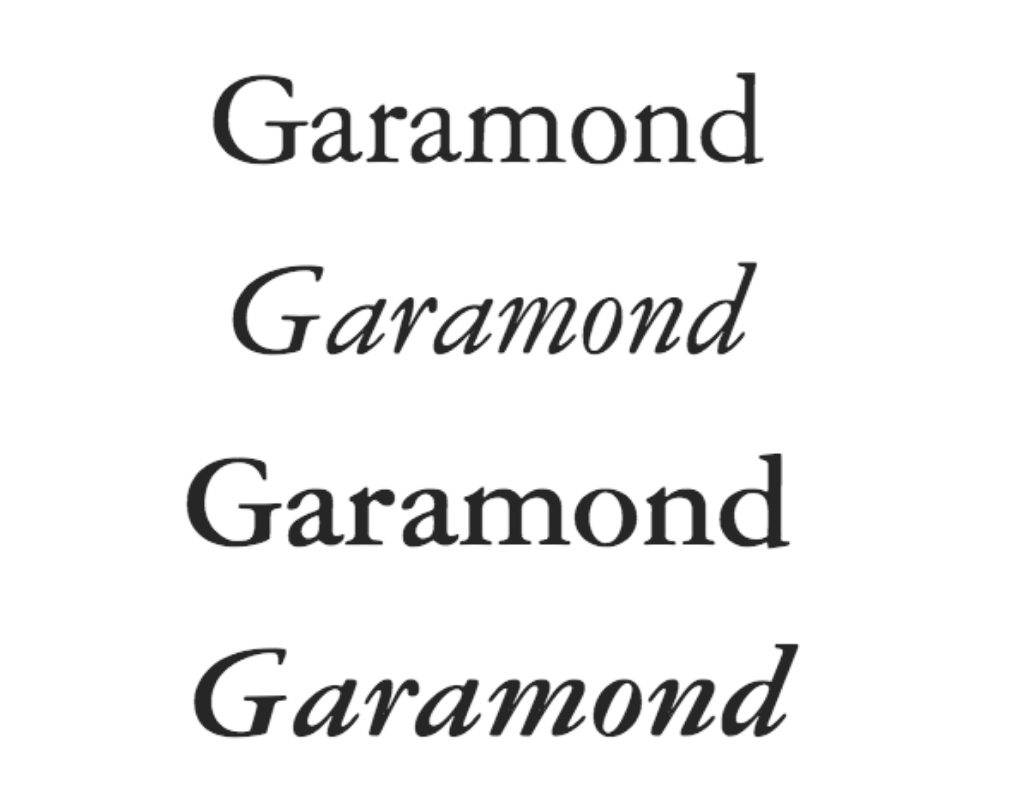
Краткий факт: это семейство шрифтов, созданное по мотивам работ выдающегося гравера 16-го века Клода Гарамонда, стало популярным в качестве стандартного варианта в Microsoft Word.
Если бы этот шрифт был персонажем: Гарамонд, детектив 1920-х годов, скрывающийся в тени переулка Нью-Йорка, ожидающий, когда коррумпированный окружной прокурор покинет ночной клуб, связанный с мафией, — прямо как дома в захватывающем триллере .
2.Caslon/ Шрифты для книги
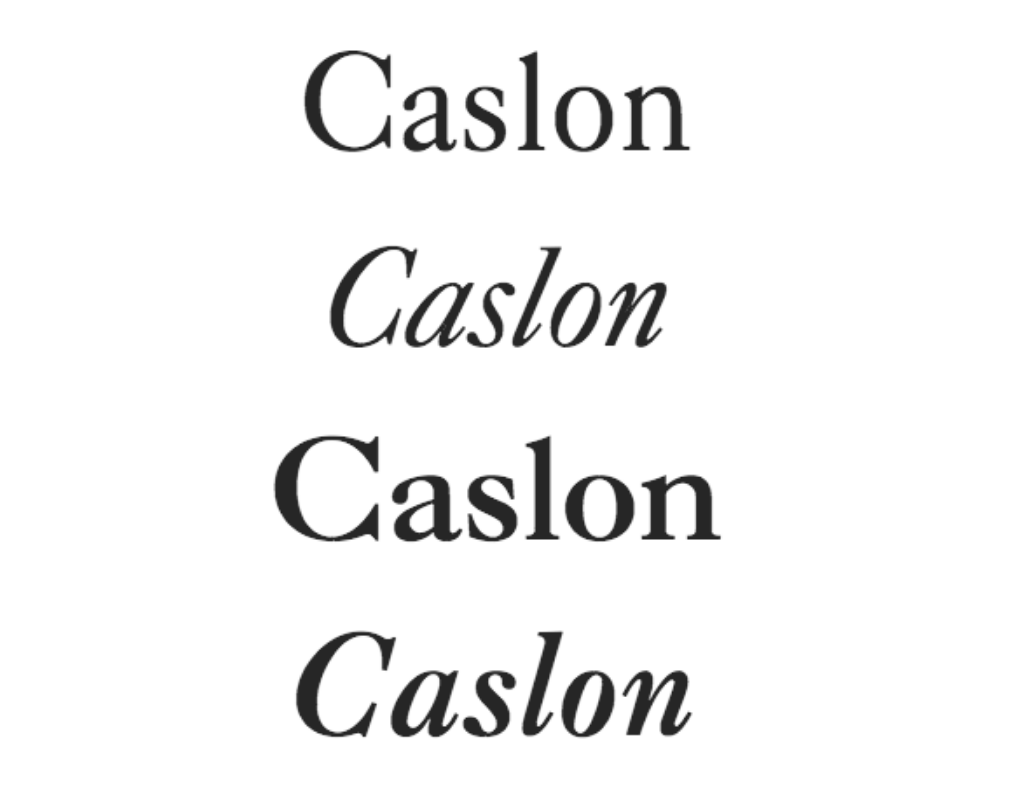
Краткий факт: дизайнер Caslon Уильям Кэслон возглавил разработку английского типографского стиля, вызвав отход от импортированных голландских шрифтов, которые были распространены в Англии в то время.
Если бы этот шрифт был персонажем: Кэслон, серьезный профессор в очках, которого до сих пор навещают бывшие студенты, потому что они чувствуют, что всем своим успехом они обязаны ему. Ясный и надежный, Caslon отлично подходит для документальной литературы .
3. Baskerville . Шрифты для книги
Быстрый факт: Баскервиль был новинкой XVIII века благодаря контрастным толстым и тонким мазкам. Джон Баскервиль, создатель этого шрифта, находился под сильным влиянием своего опыта в каллиграфии.
Если бы этот шрифт был персонажем: Баскервиль , хозяйка поместья, управляет домом, как плотным кораблем. Слуги дрожат под ее железным взглядом — но ее ледяная внешность тает, когда она садится за мольберт. Баскервиль пробирается по коридорам исторической фантастики.
4. Sabon. Шрифты для книги
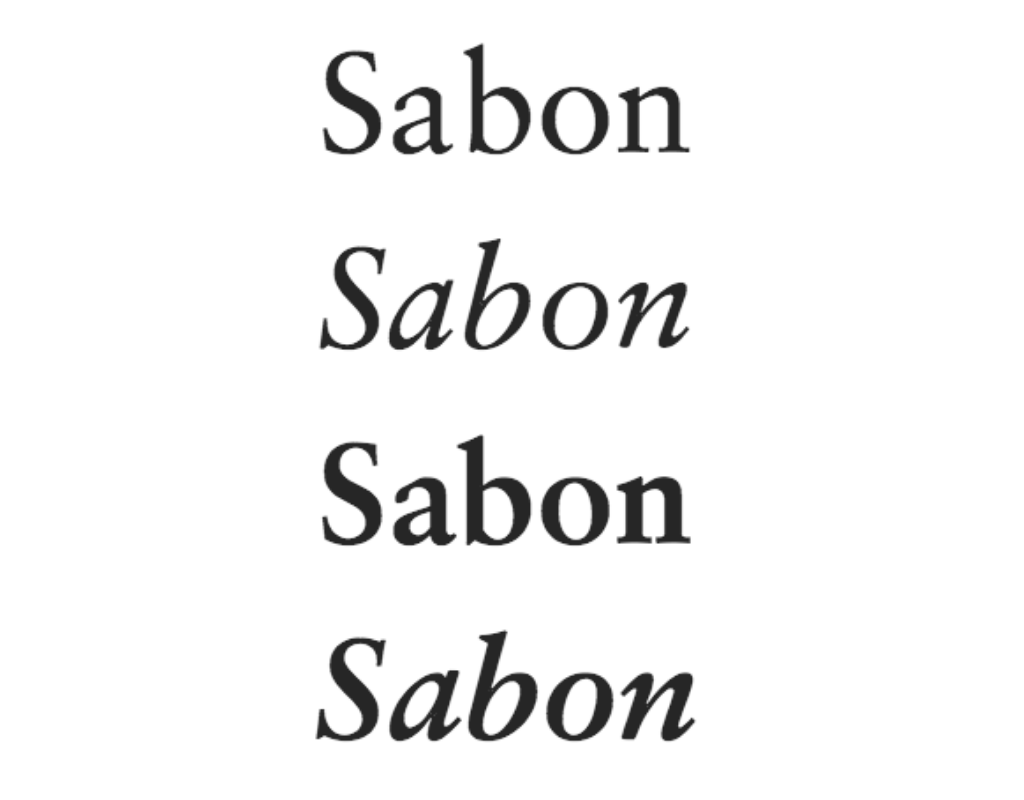
Быстрый факт: из изображения выше вы можете заметить, что каждый вариант шрифта Sabon имеет точно такой же межбуквенный интервал (или трекинг , как его называют типографы). Это следствие ограничений наборных станков для чугуна, использовавшихся на момент его разработки.
Если бы этот шрифт был персонажем: Сабон, застенчивый безнадежный романтик, крадет взгляд на возлюбленную, которая не знает своих истинных чувств, прежде чем, наконец, набраться смелости и сказать «привет». Отсюда возникает сладкий и мечтательный роман . Шрифты для книги
5. Dante
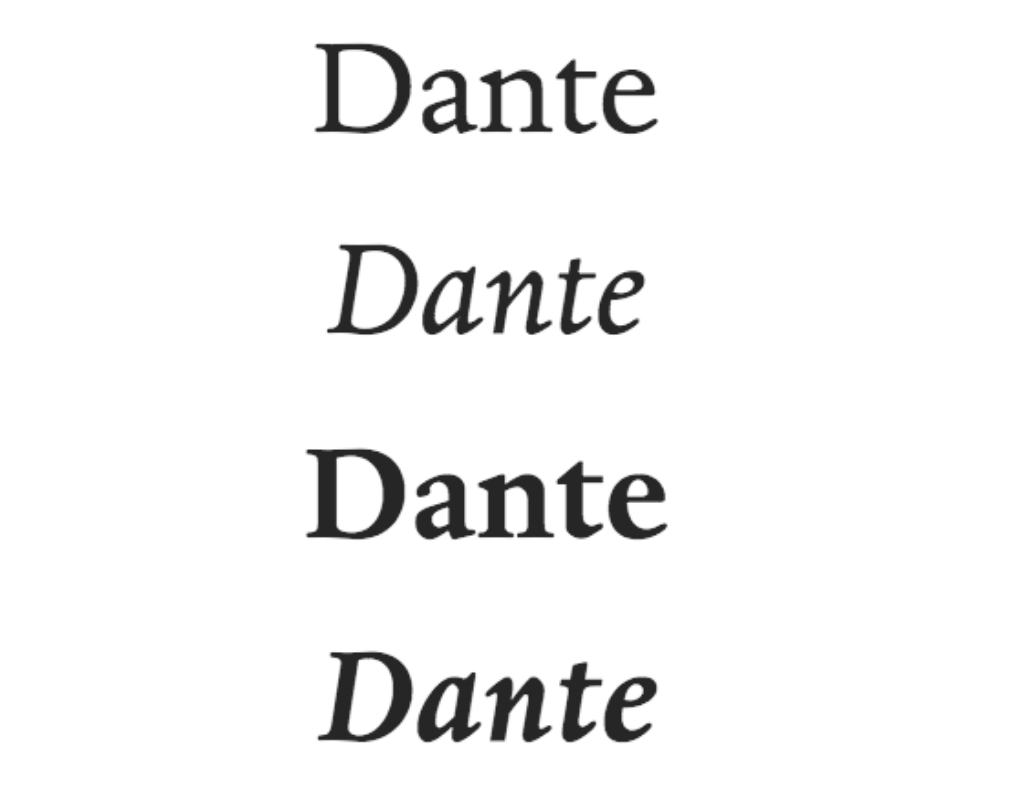
Краткий факт: Данте был первоначально разработан в середине 20-го века для эксклюзивного использования Officina Bodoni, частной прессой, которой восхищаются коллекционеры книг по всему миру.
Если бы этот шрифт был персонажем: Данте, озорным подростком, который только что нажал запретную большую красную кнопку в диспетчерской. Космический корабль кренится. Данте осмеливается отправить вас в увлекательное научно-фантастическое приключение . Шрифты для книги
6. Bembo
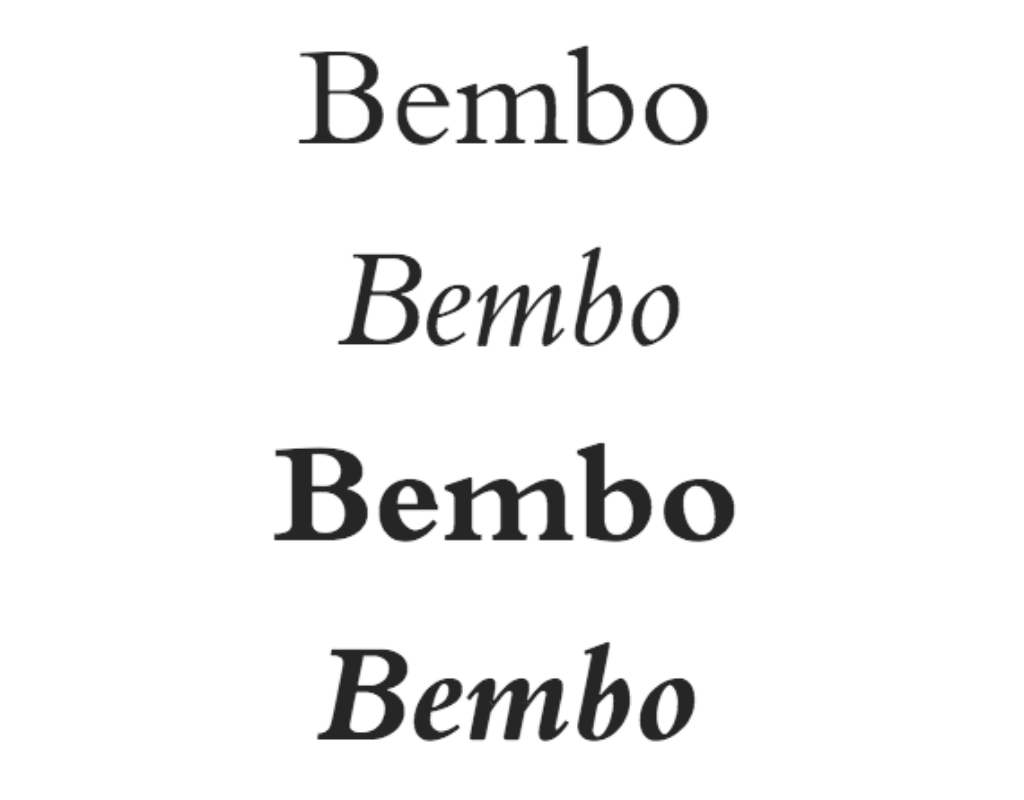
Быстрый факт: в отличие от многих гарнитур, названных в честь их дизайнеров, Bembo берет свое имя от автора, который первым использовал его в публикации: итальянского поэта Пьетро Бембо.
Если бы этот шрифт был персонажем: Бембо, увлеченный странствиями фотограф, обедающий в одиночестве в тени пальмы, третья порция жареной рыбы уже в пути — но сможет ли он действительно заполнить пропасть внутри него? Bembo — отличный выбор для запоминающейся литературной фантастики .
7. Jason/ Шрифты для книги
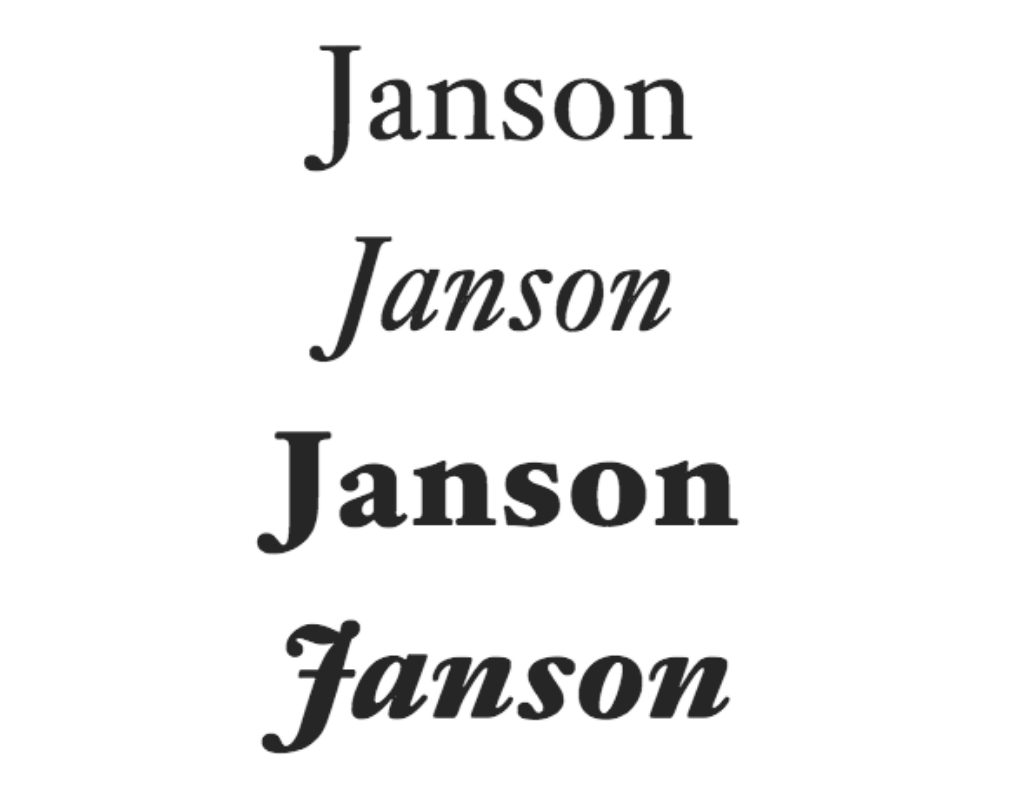
Быстрый факт: хотя этот шрифт на самом деле был разработан венгерским штамповщиком Миклошом Кисом, первоначально он был ошибочно приписан Антону Янсону, имя которого он носит до сих пор.
Если бы этот шрифт был персонажем: Янсон — мудрая старая душа, которая после долгих лет быстрой жизни музыканта променяла трубу на мастерок, в изобилии выращивая фрукты и овощи. Совершите путешествие по переулку памяти вместе с Янсоном в своих мемуарах .
8. Bison/ Шрифты для книги
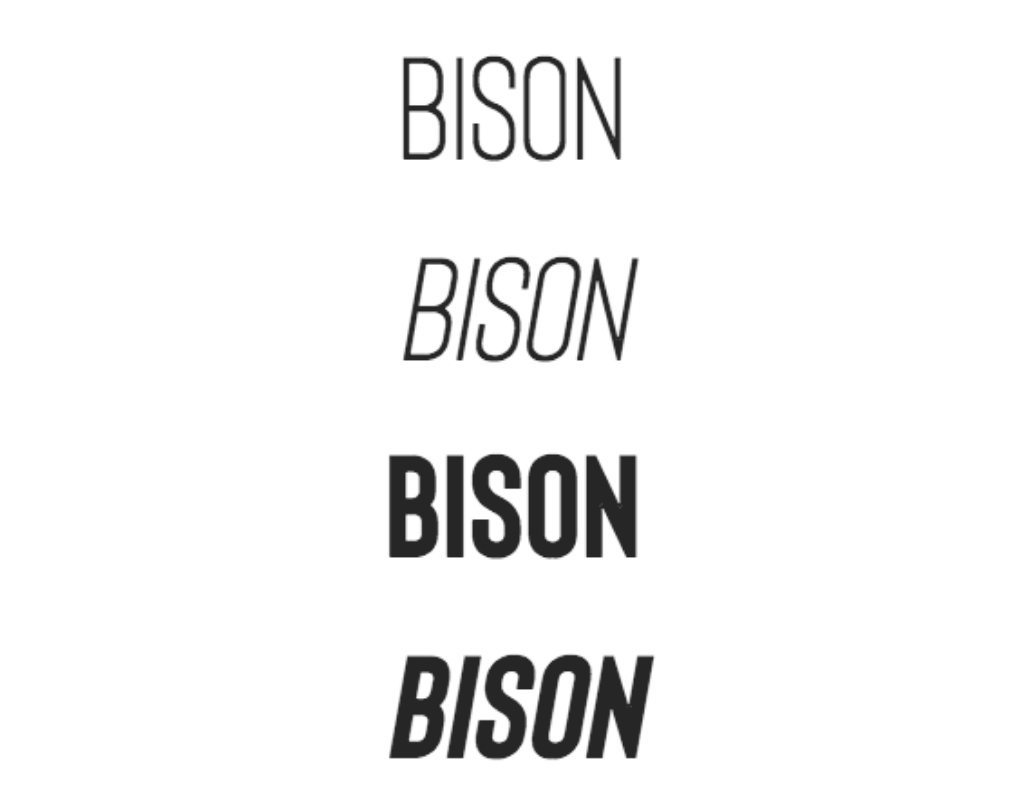
Быстрый факт: этот шрифт без засечек, состоящий только из заглавных букв, был вдохновлен животным, от которого он получил свое название. (Но, честно говоря, мы не видим сходства.)
Если бы этот шрифт был персонажем: Бизон, крупный и ответственный генеральный директор, поставил ноги на стол и смотрел на город с 90-го этажа. Bison привносит элегантность и уверенность в заголовки и заголовки.
9. Captain comic Шрифты для книги
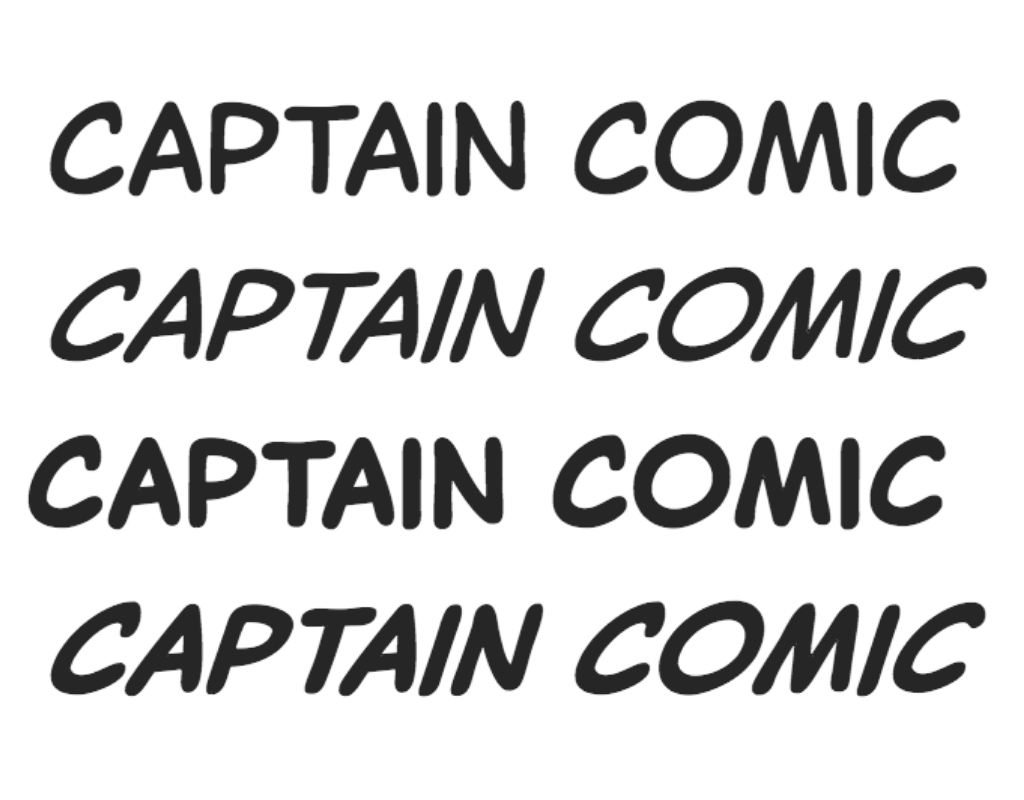
Быстрый факт: явно вдохновленный стилем букв, найденным на страницах комиксов , Captain Comic является сложной старшей сестрой Comic Sans. Используйте с осторожностью!
Если бы этот шрифт был персонажем: Captain Comic, бесстрашный герой, взбирается на башню с часами глубокой ночью — осознавая, какая опасность может поджидать наверху, но тем не менее бесстрашный. Captain Comic безраздельно властвует в насыщенном событиями графическом романе .
10. Pequena Pro. Шрифты для книги
Краткий факт: Pequena Pro была разработана в 2016 году Родриго Арайя Саласом и поддерживает как латиницу, так и кириллицу. (Послушайте, не все эти быстрые факты могут быть победителями.)
Если бы этот шрифт был персонажем: Pequena Pro, говорящий бегемот, ищет еды (как всегда), когда она встречает застрявшую на берегу семью сурикатов и предлагает помочь им пересечь реку. Pequena Pro восхитительна для детской книги .
Как получить доступ к книжным шрифтам
Самый простой способ найти наиболее подходящие шрифты для вашей книги — это обратиться к профессиональному дизайнеру. У них будет доступ к библиотекам шрифтов, и многие из этих экспертов могут даже создавать собственные шрифты , если ваш проект потребует этого.
Но если вы воспользуетесь подходом «сделай сам» к форматированию книги , тогда вам придется самостоятельно разрабатывать шрифты. Вот что нужно знать, если вы выбираете этот маршрут:
Вы не покупаете шрифт, вы его лицензируете. Если вы собираетесь печатать физические копии, а также публиковать электронные книги, вам необходимо подтвердить, что шрифт можно использовать в печати, а не только в цифровой работе (как некоторые из них). Шрифты для книги
Шрифты бывают связками. Здесь можно быстро переключиться на терминологию типографики — чтобы использовать все шрифты определенного гарнитуры (например, Caslon Regular, Caslon Bold и Caslon Italic), вам нужно купить все семейство шрифтов Caslon, по отдельности или как часть набора.
Бесплатно не всегда хорошо. Ссылки для загрузки бесплатных шрифтов иногда могут содержать вирусы. Также имейте в виду, что лицо, предлагающее бесплатный шрифт, может фактически не иметь права распространять его — и это может иметь последствия за их использование . Шрифты для книги
В связи с этим, вот несколько заслуживающих доверия сайтов, которые предлагают как бесплатные, так и платные шрифты:
Независимо от того, скачиваете ли вы шрифты бесплатно или покупаете их, обязательно внимательно прочтите Условия и положения, чтобы вы точно понимали, что вы можете и что не имеете права с ними делать.
У всех шрифтов есть время и место — да, даже Comic Sans — но этого места может не быть в вашей книге. Выполняя этот критический процесс выбора, убедитесь, что вы думаете о специфике своей книги и о том, чего именно вы хотите добиться с помощью шрифта.
Типография Азбука
Мы рады представить вам типографию «Азбука» — ваш надежный партнер в печати книг высокого качества. Мы специализируемся на профессиональной печати и издательском процессе, предлагая широкий спектр услуг для авторов, издателей и бизнес-клиентов.
Наша типография оснащена современным оборудованием и использует передовые технологии для достижения оптимальных результатов. Наш опытный и творческий персонал всегда готов воплотить в жизнь ваши идеи и помочь вам создать книгу, которая будет выделяться своим качеством и привлекать внимание читателей.
Мы предлагаем широкий выбор опций и услуг, включая цветную и черно-белую печать, различные форматы книги, разнообразные типы бумаги и обложек. Мы также предлагаем услуги верстки, редактирования текста, дизайна обложек и творческой поддержки, чтобы помочь вам достичь желаемого эстетического и качественного результата.
Наша команда гарантирует высокий профессионализм, точность и соблюдение сроков. Мы понимаем, что каждая книга уникальна, и наша цель — обеспечить ваш успех и удовлетворение от конечного продукта.
Если вы ищете надежного партнера для печати книг, обратитесь к нам в типографию «Азбука». Мы готовы воплотить вашу книгу в жизнь с безупречным качеством и профессиональным подходом. Свяжитесь с нами сегодня и доверьте нам свою печать книг.
Цена изготовления книг и блокнотов формат А5 (148х210 мм). Твердый переплет
| Тираж/Станицы | 50 | 100 | 200 | 300 |
|---|---|---|---|---|
| 150 | 216 | 200 | 176 | 163 |
| 250 | 252 | 230 | 203 | 188 |
| 350 | 287 | 260 | 231 | 212 |
Формат А5 (148х210 мм)
Обложка: палитурный картон 2 мм. Печать 4+0. (цветная односторонняя). Ламинация.
Форзацы — без печати.
Внутренний блок : бумага офсетная плотностью 80 гр/кв.м. Печать 1+1 (черно-белая печать с двух сторон)
Крепление — нитка.
Цена за 1 шт при тираже.
Цена изготовления книг и блокнотов формат А4 (210х297 мм). Твердый переплет
| Тираж/Станицы | 50 | 100 | 200 | 300 |
|---|---|---|---|---|
| 150 | 400 | 380 | 337 | 310 |
| 250 | 470 | 440 | 392 | 360 |
| 350 | 540 | 480 | 441 | 410 |
Формат А4 (210х297 мм)
Обложка: палитурный картон 2 мм. Печать 4+0. (цветная односторонняя). Ламинация.
Форзацы — без печати.
Внутренний блок : бумага офсетная плотностью 80 гр/кв.м. Печать 1+1 (черно-белая печать с двух сторон)
Крепление — нитка.
Цена за 1 шт при тираже.
Каким шрифтом печатают книги?
Выбор шрифта для книги — проблема, которая волнует начинающих создателей художественной и научной литературы.
Задача дизайнера книжной типографии состоит в том, чтобы подобрать идеальный шрифт для вашей книги. Главное правило того, что вы прогадали со стилем шрифта, — это удобство чтения. Когда вы читаете книгу, вы погружаетесь в историю, наполняетесь эмоциями автора, познаете новую информацию, и последнее, что вы должны замечать — как выглядит шрифт.
Если вы решили самостоятельно заняться оформлением рукописи, прочтите несколько важных советов по лучшим шрифтам для книги от типографии “Принтлето”.
Какой размер шрифта используется в книгах?
Шрифт — неотъемлемая часть в создании композиции книги. Книжные дизайнеры разделяют два понятия: гарнитура и шрифт.
Шрифт — это определенный образец, например, Helvetica Narrow Italic. А гарнитурой обозначают набор шрифтов одного рисунка, но разных размеров (кеглей) и начертаний. Например, Helvetica — это гарнитура.
Шрифт также делят на 2 группы: наборный и рисованный. Наборный шрифт используется для самого текста издания. Рисованный шрифт применяется для визуального оформления, дизайна книги, в частности, на обложке, переплете и титульном листе. Рисованный шрифт создает уникальный стиль книжного произведения.
При выборе шрифта учитывайте 3 особенности: гарнитуру, начертание и кегль.
Наборный текст рекомендуется печатать обычным, курсивным, полужирным или курсивным полужирным шрифтом в выбранной гарнитуре. Добиться запоминающегося дизайна можно используя всего пару шрифтов.
Что ещё влияет на выбор шрифта? Конечно, бумага. Если у вас мелованная бумага, то не используйте тяжелые, контрастные шрифты, они выглядит броско. А на газетной бумаге с трудом читается тонкий и изящный шрифт.
Чтобы вашу книгу смог прочитать каждый без лишнего напряжения и «вглядывания» в буквы, важно подобрать шрифтовой кегль. Размер кегля исчисляется в пунктах (1 пункт = 0,376мм).
Для каждого кегля есть свое персональное название: кегль 6 пунктов — бриллиант; кегль 4 пункта — диамант; кегль 6 пунктов — нонпарель; кегль 7 пунктов — миньон; кегль 8 пунктов — петит; кегль 9 пунктов — боргес; кегль 10 пунктов — корпус; кегль 12 пунктов — цицеро; кегль 14 пунктов — миттель.
Для каждого типа книжного издания определен наиболее читаемый размер кегля. Так, для художественной литературы подходит 10-12-ый кегль. Для остальной печатной продукции оптимальным считается 9-14-ый кегль.
Не забывайте и о том, что размер наборной строки тоже играет свою роль в удобочитаемости. Рекомендуем использовать не более 50-55 знаков в одной строке.
На выпуск книжных изданий существует ГОСТ, по которому определяется кегль и стиль шрифта. В большинстве печатных изданий используют Times New Roman, Garamond, Bodoni, Academy, Georgia.
Роль шрифта в оформлении книги
Шрифт — способ передачи текста в книге. Это его главная и существенная роль. Подобрать должным образом шрифт — задача непростая, но по силу каждому. Следуйте простым правилам подбора шрифта, и тогда всё получится. А ниже мы подобрали основные принципы, на которые влияет шрифт.
Шрифт с засечками и без. Для основного текста издания рекомендуем использовать шрифт с засечками или без засечек, потому что такие шрифты являются «классическими» и не вызывают дискомфорта при длительном чтении. Декоративные шрифты подходят для заголовков, оглавления или других элементов книги, на которых нужно заострить внимание.
Ненавязчивость. Подбирайте шрифты без сложных буквенных форм. «Кричащие» о своей уникальности шрифты отвлекают читателя и не дают сосредоточиться на мысли, которую преподносит автор в тексте.
Печатные шрифты. Courier и другие шрифты, которые используются в печатных машинках, — это моноширинные шрифты. Отличить их можно по одинаковой ширине всех знаков. Избегайте таких шрифтов для создания основного текста книги. В качестве исключения, моноширинные шрифты используют для заголовков глав, и в других случаях, где вам требуется характерный шрифт.
Как выбрать шрифт для детской книги?
Если вы пишите детскую книгу и не знаете, какой размер шрифта лучше подойдет, то прочтите рекомендации по выбору шрифта для каждой возрастной группы. Для детей дошкольного возраста (до 7 лет) подойдет шрифт в 16 или 20 пунктов, так как дети только начинают читать и знакомиться с буквами, их должно быть хорошо видно.
Для детей первой младшей группы (7-9 лет) 14 и 16 пунктов для первоклассников, 12 и 14 пунктов для второго класса.
Для детей второй младшей группы (10-11 лет) 11 и 12 пунктов для третьего класса, 10 и 11 пунктов для четвертого класса.
Дети среднего и старшего возраста (12-17 лет или 5-11 классы) могут читать шрифт любого размера.
Лучшие шрифты для чтения на электронной книге eBook
При чтении электронных книг приходится проводить много времени уставившись в экран. Поэтому внешний вид текста имеет большое значение! Правильный выбор шрифта может улучшить общее впечатление от чтения. Какой шрифт поможет вам читать быстрее и меньше напрягать глаза? Когда речь заходит о шрифтах, выбор очень велик. Некоторые шрифты приятны для глаз, некоторые обладают индивидуальностью, а некоторые легко читаются.
Если в вашей электронной книге много текста, самыми удобными для чтения будут шрифты с засечками, такие как Times New Roman, Garamond, Baskerville и Caslon. Эти старые традиционные шрифты уже давно используются для книг и по-прежнему являются отличным выбором для электронных книг. Важно, чтобы шрифт был удобен для чтения, тем более что люди будут читать его в цифровом формате на экранах любого размера. Шрифты с засечками более разборчивы и привлекательны для читателя.
Вот несколько лучших шрифтов, которые эксперты рекомендуют для электронных книг.
Как правильно выбрать шрифт для книги?
— Конечно, книга — это, в первую очередь, носитель информации и хранитель знания. Но в культуре всегда важна коммуникация. И графический дизайн в определенном смысле осуществляет функцию перевода. С читателем необходимо коммуницировать. Если дизайн хороший, он облегчает доступ к культуре. Если он сделан плохо и небрежно, культурный материал рискует быть утраченным.
— Получается, что, издавая книгу в переводе на другой язык, дизайн книги также нужно определенным образом «переводить»?
— Существуют вещи, которые можно передать «один к одному». Например, для книги, изданной на немецком языке, существуют правила набора текста или форматирования, которые можно «перевести», работая с кириллицей. В некоторых своих книгах я часто обращаюсь к метафорам в концептуальной структуре издания, разным возможностям построения в нем нарратива. В одной моей работе, например, один рассказ воспроизводится трижды, но с различных точек зрения. Такие вещи будет легко адаптировать при «переводе». Однако кое-что (например, ту же типографику), вполне вероятно, придется переделать полностью.
— Может ли профессиональный дизайнер иметь свои предпочтения в смысле материала, с которым работает, или же он должен уметь спроектировать издание на любую тему?
— Мое собственное мнение всегда играет существенную роль. Есть клиенты, с которыми я ни за что не стал бы сотрудничать, с другими по завершении работы мы становились хорошими друзьями. То же касается изображений. Работа по их отбору всегда внушительна и масштабна. Например, во время работы над одной книгой на нас свалилось около десяти тысяч произведений одного художника, но в издании мы смогли опубликовать лишь шестьсот. В этом случае, конечно же, мы глубоко были вовлечены в процесс отбора.
Толщина шрифта придает «толщину» и вес самому изданию. Книга становится высказыванием. И это важно, потому что она посвящена сквотам, уличным протестам, демонстрациям.
— Мой вопрос скорее о специализации.
— Область, которой я занимаюсь, можно обозначить как «книги и бренды» (books and brands). Кроме того, я преподаю дисциплину, которая называется «дизайн изданий» (editorial design). Это очень широкое понятие: сюда входят не только книги, но и газеты, журналы и в некотором смысле движущиеся изображения, если включить сюда еще и интернет-сайты. С другой стороны, мой интерес определенным образом сфокусирован, потому что моей страстью является создание и написание шрифтов.
Не могу сказать, что круг сотрудничества студии Hubertus Design, где я работаю, очень узок. Мы работаем с архитекторами, художниками, учеными, выпускаем литературные и экономические издания и не только. Современному графическому дизайнеру необходимо ориентироваться в огромном массиве информации. Одновременно с этим существует спрос на специализированный, узко заточенный дизайн для конкретных профессиональных областей. Часто мы работаем внутри разветвленных сетевых структур. Разумеется, ты не можешь уметь все, но ты должен понимать, где найти необходимую информацию и как связаться со специалистом, помощь которого тебе в данный момент необходима.
— Вы говорили, что дизайн выступает в роли переводчика. Но при этом в другом месте вы высказывали мнение, что значительная часть графического дизайна очень провинциальна. Может, она просто отражает особенности конкретной локальной культуры?
— В моих словах нет никакого противоречия, потому что дизайн, который я называю провинциальным, не имеет отношения к местной специфике. Если работа отвечает характерным локальным запросам, проблемам или вызовам, я всячески это приветствую. Но «провинциальное», напротив, несет в себе наиболее неспецифическое. Такие вещи обычно проходят по ведомству декора. Они поверхностны, непродуманны, и за ними не стоит никакой определенной позиции.
— Хотел спросить вас про конкретную книгу, выпущенную студией Hubertus Design, — издание «Wo-Wo-Wonige». Оно представляет собой докторскую диссертацию Томаса Штаеля, посвященную активистским движениям в Цюрихе после 1968 года. Как по-вашему, может ли дизайн сам по себе выполнять критическую функцию, быть критическим?
— Конечно, да, очень даже может. В некотором роде он всегда таковым и является. Дизайн всегда был тесно связан с вопросами политики. С другой стороны, если речь заходит о дизайне изданий или книг, пространства для маневров остается не так много. Дизайн ни в коем случае не может становиться барьером между читателем и текстом, но должен «поддерживать» передаваемое содержание. И если он сам вдруг начинает перевешивать, он просто перестает работать.
Книга «Wo-Wo-Wonige», которую вы упомянули и которая получила Федеральную швейцарскую премию в области дизайна, в этом смысле особенно интересна. Во-первых, она достаточно легко написана. Во-вторых, была проделана огромная работа. Автор посвятил ей много лет и собрал уйму материала, который, конечно же, невозможно было опубликовать в издании целиком. Текст в ней набран шрифтом Monotype Grotesque BoldExtended. Этот яркий полужирный шрифт, и в текстовых изданиях он обычно никогда не используется. Именно за это мою работу больше всего критиковали — что книга толщиной почти в пятьсот страниц отпечатана подобным образом.
Чем c более ярким и гетерогенным материалом ты работаешь, тем скромнее тебе приходится быть как дизайнеру.
Книга при этом получилась очень читабельной. Она настраивает на очень хороший темп и скорость восприятия. А толщина шрифта придает «толщину» и вес самому изданию. Книга становится высказыванием. И это важно, потому что она посвящена сквотам, уличным протестам, демонстрациям. Было бы просто неверным использовать более «мягкий» шрифт для такой импульсивной и агрессивной темы.
При этом, делая книгу, я полностью отказался от курсива. Если какой-то фрагмент нужно было выделить, я использовал шрифт печатной машинки. Таким образом, текст, набранный Monotype Grotesque Bold Extended, который получился довольно темным, был «усеян» подобными как бы машинописными вставками. Это, в свою очередь, отсылало к техникам, популярным в 70-е и 80-е, — коллажам, вырезкам и т.д.
На мой взгляд, это и есть удачный пример того, как с помощью дизайна удалось подчеркнуть нечто важное в самой книге.
— В данном случае вы работали c научным текстом. Как быть дизайнеру, который делает каталог художника или архитектора, вещь яркую и выразительную в плане визуальности?
— С одной стороны, чем c более ярким и гетерогенным материалом ты работаешь, тем скромнее тебе приходится быть как дизайнеру. Но все сильно зависит от ситуации и художников, чьи книги ты проектируешь. Иногда, если материал слишком выразительный и кричащий, бывает полезно перегнуть палку и местами переборщить. Но такие вопросы всегда лучше решать в сотрудничестве с клиентом.
— Последний вопрос — каковы взаимоотношения дизайна и рынка?
— Это большая тема, и в Швейцарии очень много дискуссий ведется по этому поводу. Швейцарский дизайн долгое время был связан с крупными международными компаниями, например, в области фармакологической индустрии. Связь была очень тесной, и благодаря этому местный дизайн смог быстро и широко распространиться буквально во всем мире. В 1980-е, когда большие дизайнерские компании как раз начали процветать, крупные экономические институции больше нуждались в консультантах, помогавших им выстраивать имиджевые стратегии в публичной сфере. Речь шла именно о консультантах, и дизайнеру в этой цепочке отводилась самая последняя роль. Но если консультант не имеет об этой области ни малейшего представления, то дизайн лишается возможности использовать и сотую долю своего потенциала. Невозможно заниматься только своей областью. Дизайнер должен быть вовлечен во все процессы формирования стратегий коммуникации.
Возьмем, например, типографику. За последние несколько лет эта область превратилась в огромный рынок. Она преодолела громадный разрыв, из сугубо специализированной области графического дизайна превратившись в систему коммуникационных и экономических процессов. И, я надеюсь, это послужит хорошим примером для графического дизайна в целом.